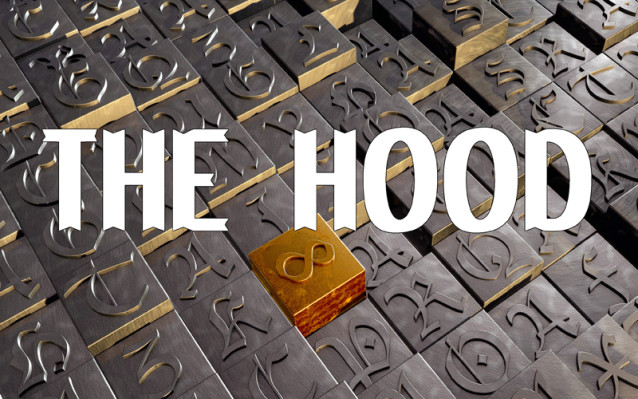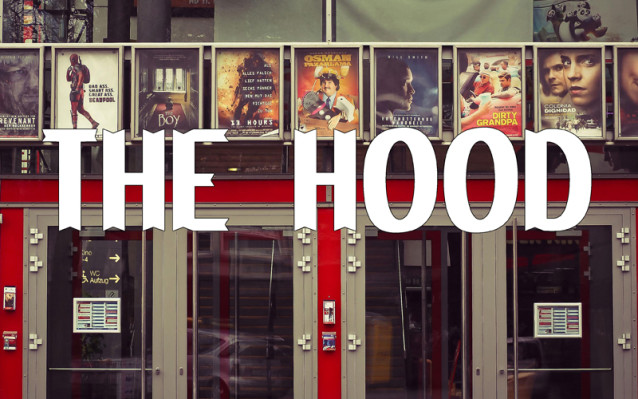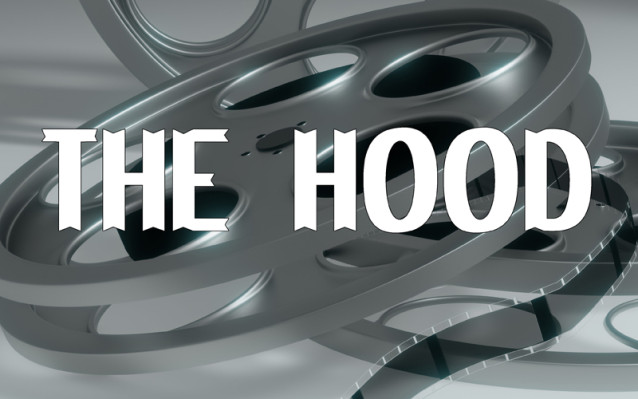
The Hood Font
LA LEGGENDA DI ROBIN HOOD font: direttamente dal film diretto da Michael Curtiz e interpretato da Errol Flynn, il font inedito per tutti gli estimatori del film. Da notare il ritocco necessario in Photoshop per conferire, alla titolazione, l’originale bordatura.
THE ADVENTURES OF ROBIN HOOD font: directly from the Best movie by Michael Curtiz, with Errol Flynn, the original font for all lovers. Use ADOBE Photoshop for the original border from title.